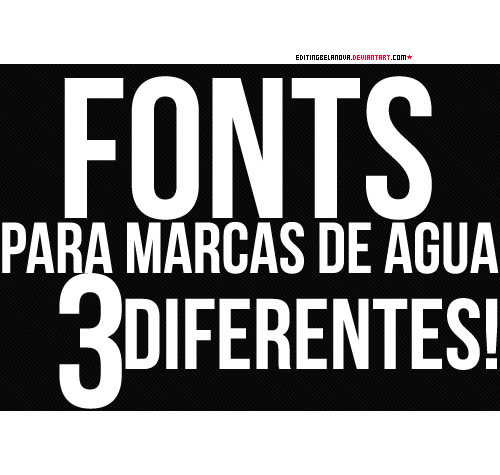
muy bien me gusta como se ven (: pero,una pregunta,como se llama la fuente que usaste para hacer esta imagen?
se llama BEBAS NEUE
Me encanto(: pero la Skinny! de que tamaño la pones para que se vea bien?
gracias, el tamaño lo pongo de 8 y sin suavisado.